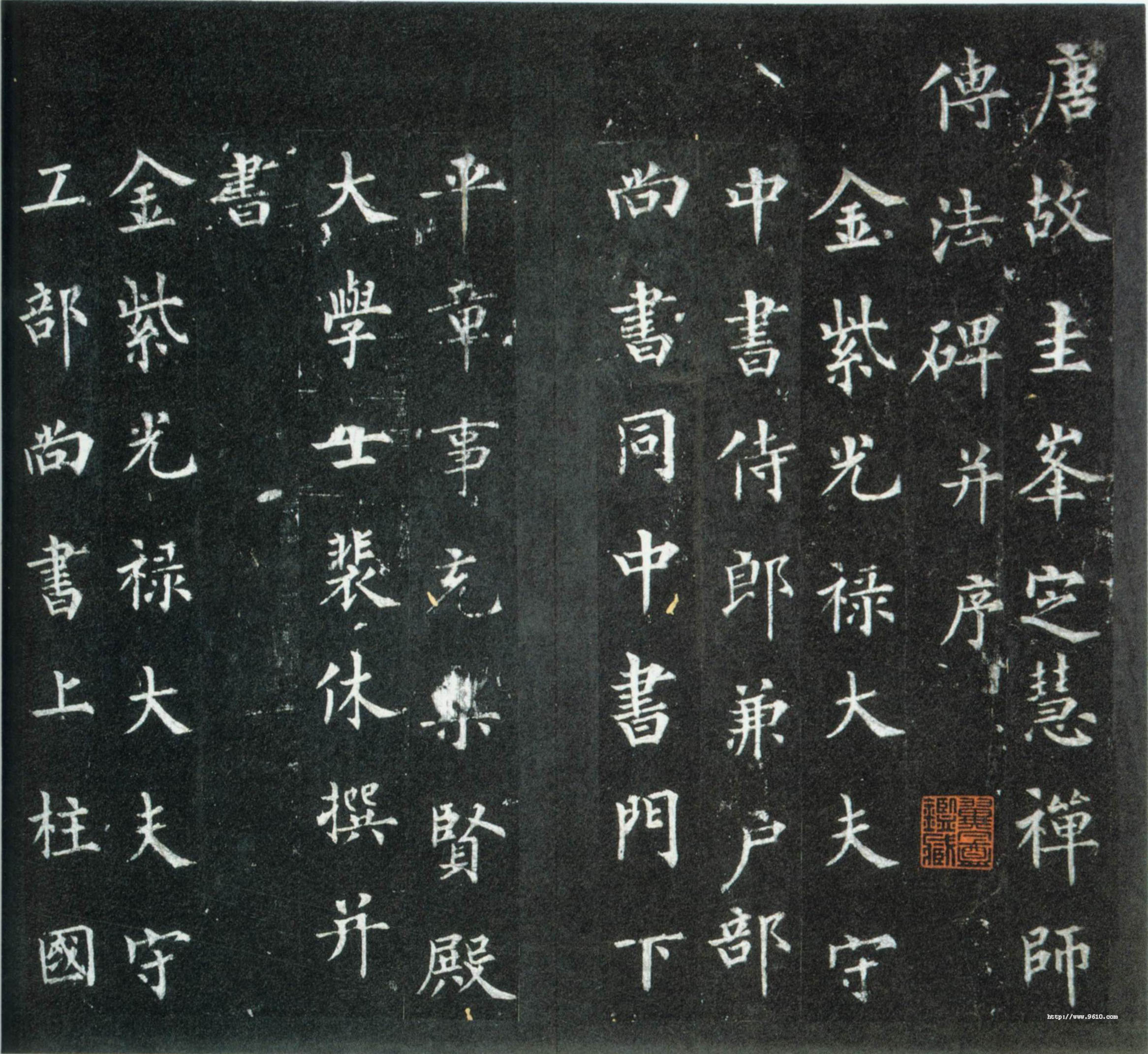
裴休简介
字公美。唐孟州济源(今属河南省)人,曾为监察御史,宣宗时进同中书门下平章事(宰相),后罢为宣武军节度使,封河东县子。后历昭义,河东,凤翔,荆南四节度。能文,工正书。寺刹多请其题额,河南庐山亦多题铭。风格遒媚有体法,为晚唐著名书家,然存世书迹仅有《圭峰禅师碑》。
作品欣赏:《圭峰禅师碑》
《定慧禅师碑》全称《唐故圭峰定慧师传法碑》,亦称《圭峰碑》。唐大中九年(八五五)十月立,裴休撰并书,柳公权篆额。碑现存陕西户县草堂寺。正书,三十六行,行六十五字,额篆书九字。
此碑笔笔谨严,清劲潇洒,结构尤为精密,取法于欧、柳,是唐碑珍品。
相关评论:米芾《海岳名言》评:“裴休率意写碑,乃有真趣,不陷丑怪。”
叶昌炽《语石》云:“《圭峰禅师碑》尚存,其书遒紧而无蕴藉,学之易滋流弊。细参之,其运笔之操纵、结体之疏密,与诚悬昕合无间。”
明王世贞《弇州山人稿》谓:“清劲潇洒,打得率更笔意。”
金代礼部尚书赵秉文这样描述此碑:“下马来寻题壁字,拂尘先读草堂碑。平生最爱圭峰志,唯有裴公无愧辞。”